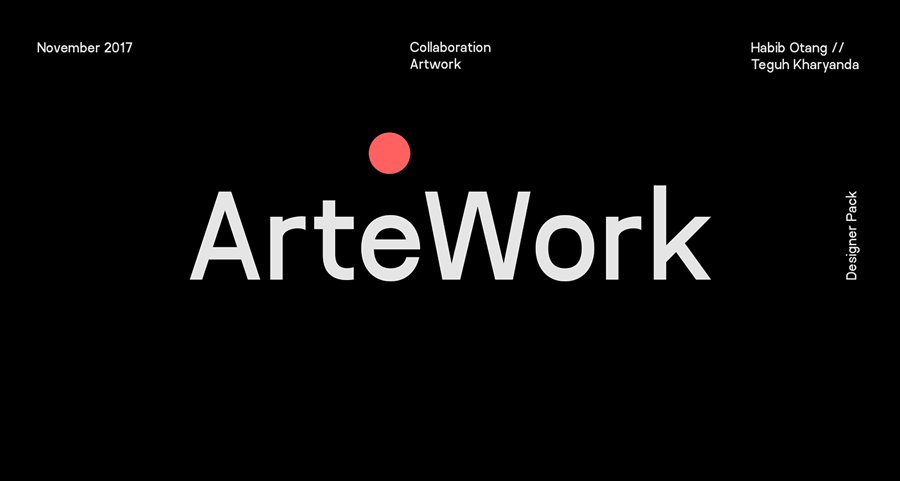
A Bifocals Font Family é uma família de fontes sans-serif desenvolvida pelo designer Habib Otang, inspirada na arte minimalista, geométrica e contemporânea. Ela foi projetada em colaboração com Teguh Kharyanda para criar um conjunto único de quatro familias que oferecem uma paleta vasta e versátil para designers. A Bifocals Grotesk é a mais recente adição à família, desenvolvida por Habib Otang inspirado nos estilos modernos e na era industrial da tipografia e design gráfico. A Bifocals Font Family está projetada para fornecer uma solução perfeita para os designers que buscam destacar seus produtos. Com sua configuração ligeiramente condensada, ela se destaca como excelente para headlines, títulos de produto, embalagens e marcas. Suas linhas finas e robustez permitem a criatividade nos desenhos de logo, assim como no design de página ou em aplicações digitais. A Bifocals Grotesk é especialmente versátil e moderna, perfeitamente adaptada para textos grandes como headlines e títulos de páginas. É uma escolha inteligente para designers que buscam um estilo contemporâneo e elegante para seus projetos.